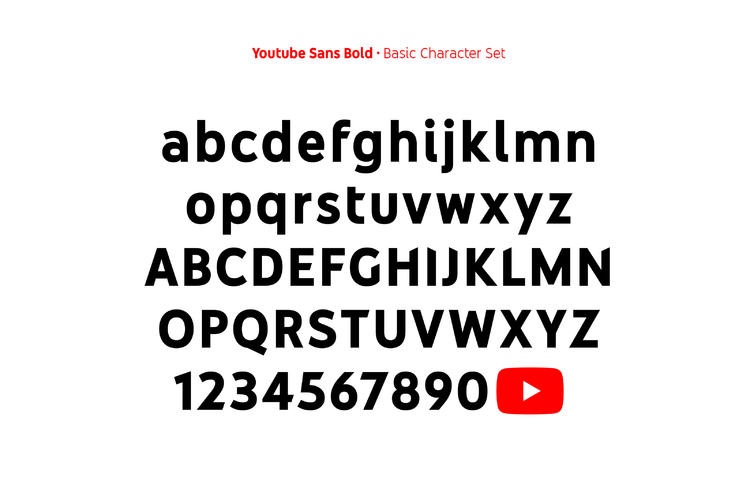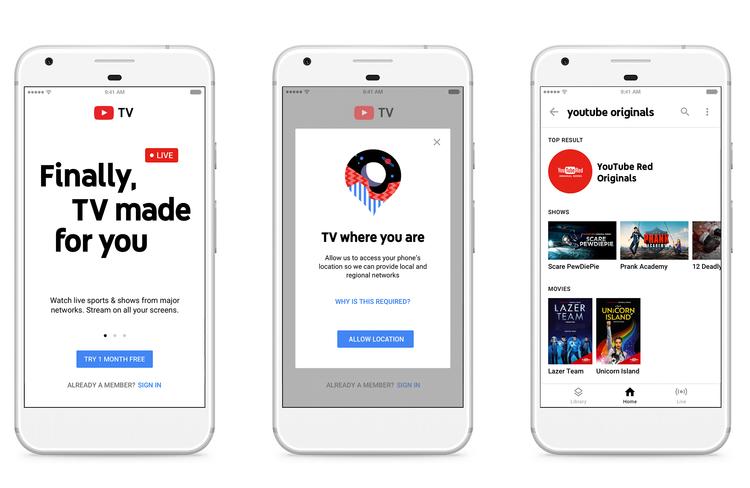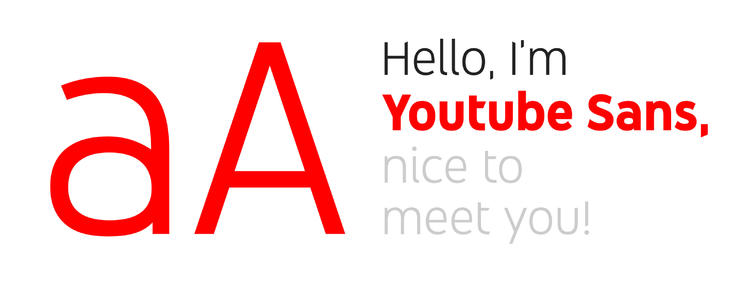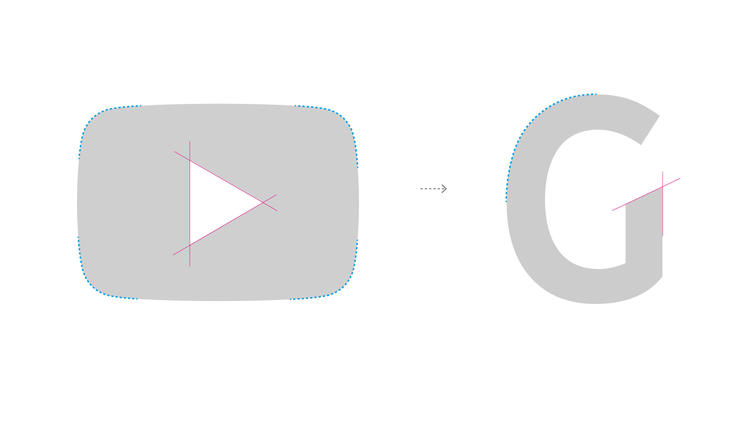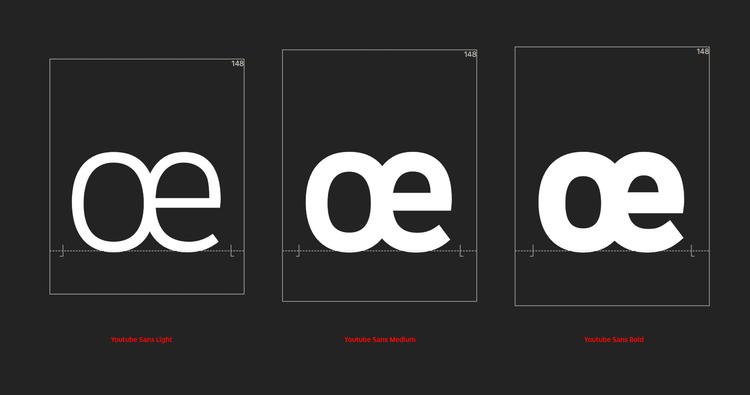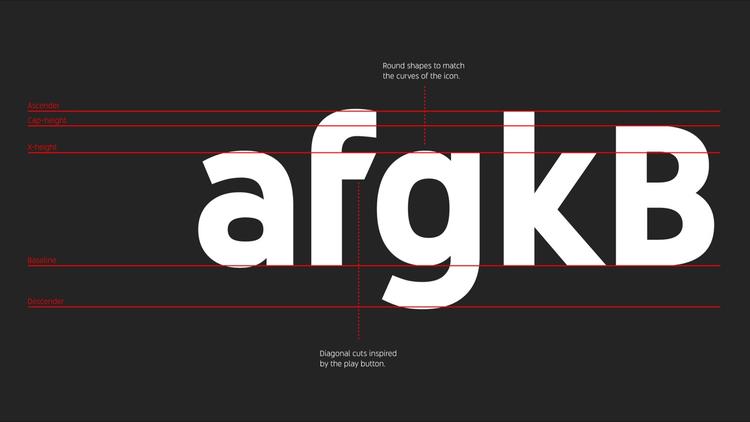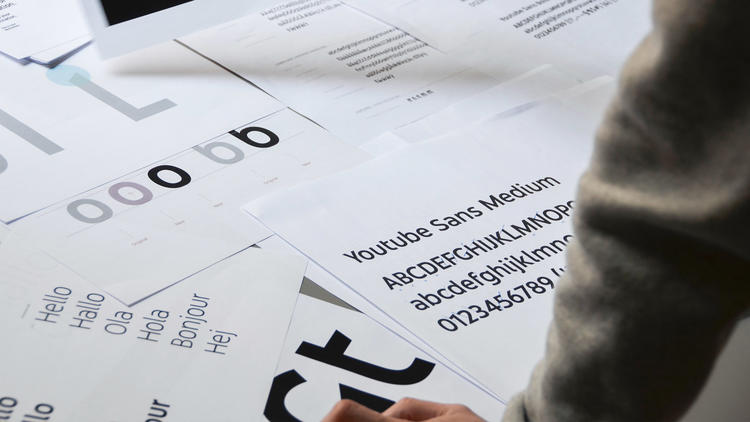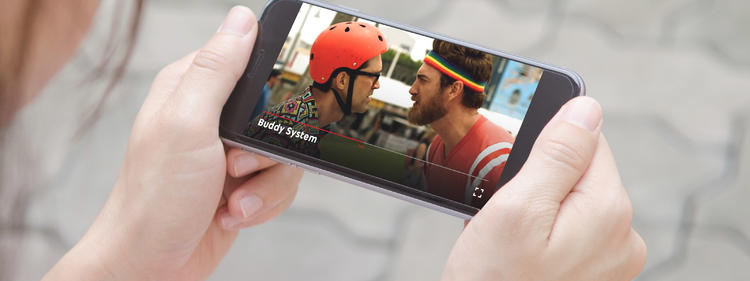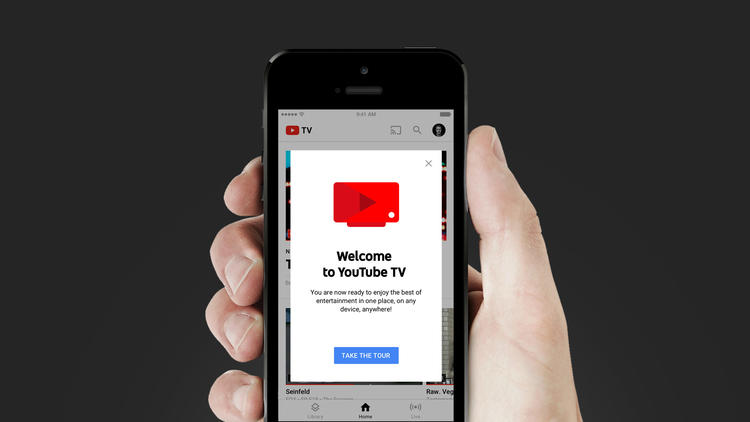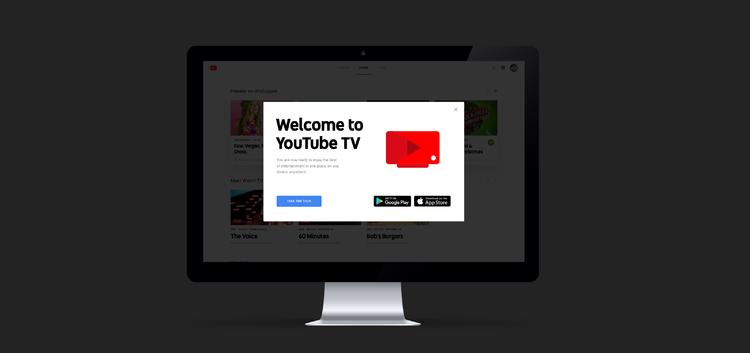
YouTube 专属字体,据说灵感来自“播放键”
“为了传播 YouTube 独特的视觉美学。”
过去,往往是一个品牌带红了某一款字体,比如 BBC 使用的 Gill sans 就是个很好的例子。但如今,有实力的公司喜欢请设计公司为自己专门开发一套字体——好奇心日报刚刚报道过迪拜政府与微软合作开发了一套名叫“Dubai”的专属字体,现在,视频网站 YouTube 也跟进了。
YouTube 开发的字体就叫 Youtube Sans,在今年 2 月 YouTube 于洛杉矶举行的 YouTube TV 上公布于众,它将会被用于 YouTube TV 和此后的新产品上。
字体的设计方是来自英国、分部设立于全球的品牌咨询公司。它由有建筑学背景的设计师 Jacob Benbunan 与著名设计公司 Wolf Olins 的联合创始人之一 Wally Olins 共同创办。Saffron 擅长于设计品牌形象,他们的客户还包括可口可乐、富士、西班牙伏林航空、澳大利亚酒精药物基金会等。
整套字体是 Saffron 与 YouTube 的用户体验设计团队一起完成的,过程中还得到了来自西班牙的字体设计工作室 Letterjuice 和德国字体公司 URW++ 的协助。
根据 Saffron 对项目的描述,双方的第一个任务是重新绘制了红色的播放键,以确保新的标志拥有更合适的比例和角度。同时,更新后的播放键标志将成为一个和其他字母一样能够被键盘输出的字符,属于 Youtube Sans 中的一员。
播放键也是这套字体的视觉核心。设计团队利用正中央白色三角形的三个斜角角度作为字母结尾处的倾斜角设计。整套 Youtube Sans 是无衬线字体,拥有细、中等、粗、特粗四个笔画选择。
Youtube Sans 现在主要被运用在 YouTube TV app 中。Saffron 表示,设计 Youtube Sans 中的一个重要标准是:它一定是一套适合于屏幕上观看的、清晰的、大胆的字体。
“像 YouTube 这样的品牌,版式是吸引用户注意力的一个重要关键。”Saffron 的创意总监 Gabor Schreier 说道:“我们必须在 YouTube TV 发布前就把字体的每一个细节都做好,因为它是这款软件中连接所有频道、以及频道上的接触点的唯一视觉要素。”